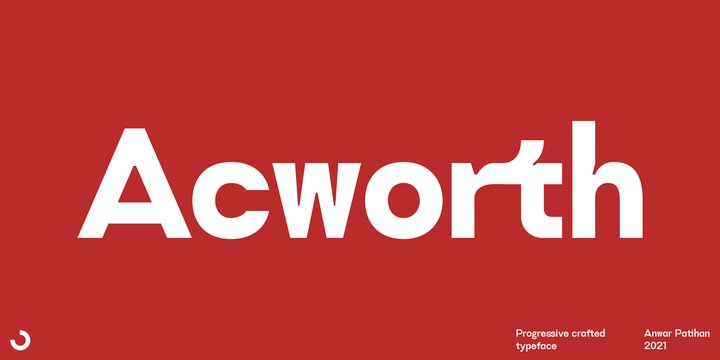
Acworth - это современный прогрессивный шрифт, который исследует механическую прочность и динамизм. Вдохновленный продвижением культуры быстрых технологий. Персонажи имеют чернильную ловушку, которая делает Acworth очень разборчивым и выделяющимся, тем самым создавая современную универсальную форму.
Сделать его пригодным для редактирования, графического дизайна, веб-просмотра, цитат или в качестве логотипа.